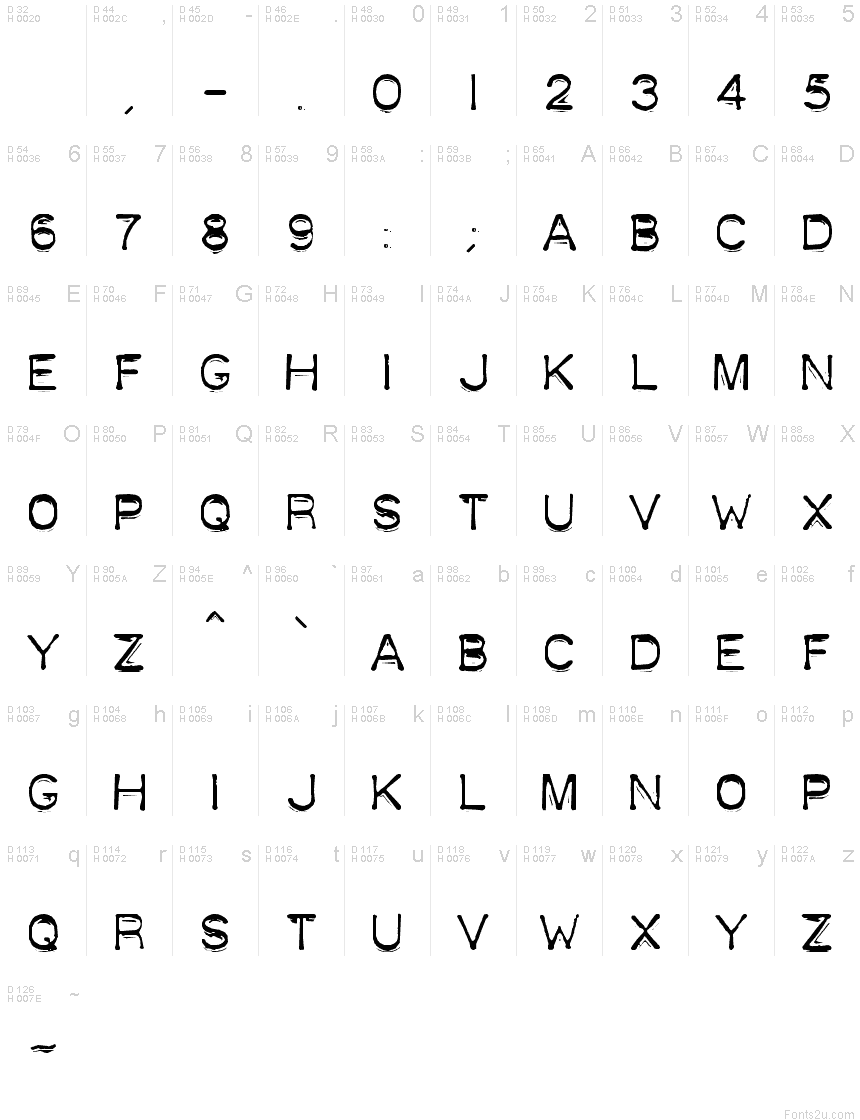
Plastique autorstwa Jeffa Vorzimmera to bezpłatny, zniekształcony krój display pisany wielkimi literami, o surowym, ręcznie wycinanym charakterze. Litery wyglądają jak uformowane i lekko wygięte, z tępymi końcówkami, chwiejnymi krzywiznami i poszarpanymi krawędziami wewnętrznymi, co nadaje alfabetowi miękki, ciężki i nieco niestabilny wygląd.
Dzięki temu krój ten doskonale sprawdza się na plakatach, okładkach płyt, zinach, planszach tytułowych i krótkich nagłówkach, gdzie wielkie litery samodzielnie budują dziwną, namacalną atmosferę. Jako darmowy font, Plastique pasuje również do logo, monogramów i wyrazistych nagłówków, które wymagają krzywej, niemalże roztopionej sylwetki, a nie czystej, geometrycznej formy.